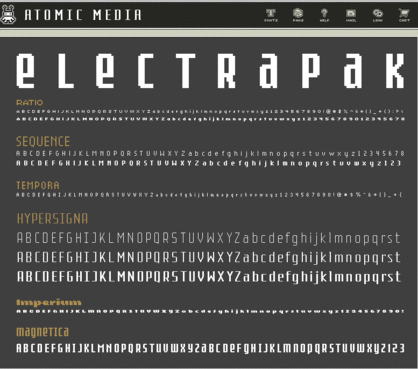
atomicmedia est une petite fonderie numérique qui propose des alphabets bitmap.
Lisibles ou pas, il s’agit bien d’une mode d’expression qui est née avec Zuzanna Licko (d’Emigre) dans les années 80. Aujourd’hui les outils typographiques très abordables permettent de multiplier à l’infini les styles et les variations. Il n’empêche que leur utilisation confère à un texte pour peu que ces alphabets soient bien utilisés, c’est à dire de façon très structurée, architecturée, un air de modernité indiscutable. En rupture totale avec l’écriture humanistique du 15e siècle. En France Pierre di Sciulio avait déjà expérimenté ces expressions à la fin des années 80.